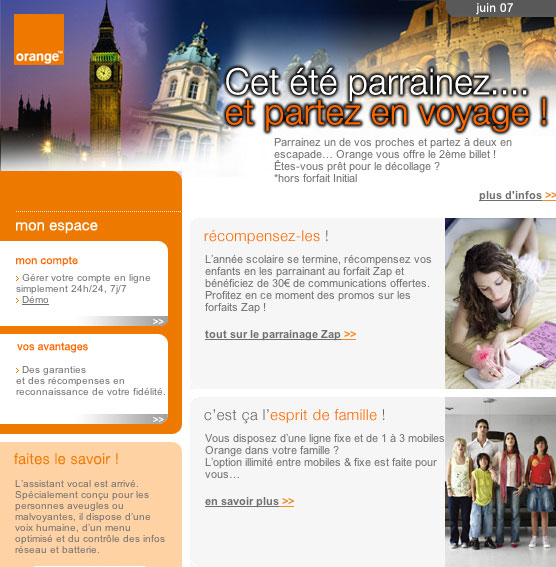
Comment définir la laideur. Une affaire difficile. Lorsqu’on regarde cette typo Helvetica «éclairé» par logiciel et ombrée floutée de même, n’importe comment, sans aucune élégance ni discernement, l’on en vient à se dire que le marketing direct sur le web est devenu l’affaire des amateurs et non plus des professionnels du graphisme. Mettez un ordinateur entre toutes les mains… Et alors, c’est bien, la modernité, la techno-démocratie. Qu’avons-nous à faire de compter des dizaines d’écoles d’Arts Graphiques dont aucun professeur n’aurait permis un tel massacre. Des centaines de DA et Directeurs de la Création qui n’auraient jamais laissé passé un «poulet» de la sorte. J’adore ce métier, tant il prolonge nos sensibilités artistiques, mais là quelle satisfaction, pour qui, pourquoi? Où est la charte graphique d’Orange, je veux la voir, la parcourir. Eh oui les designs-groups vendent très cher des chartes pour l’utilisation des logos mais qu’en est-il de l’aspect général et particulièrement de la typo des communications print ou web. Rares sont les dircoms qui supervisent dans le détail ces dévoyements taillés à la serpe. Mais si Orange continue, je vais changer d’opérateur, ç’est sûr. N’importe quel lecteur de ce blog aurait fait mieux, plus élégant, plus «propre», plus professionnel. Avis de tempête sur les services d’Orange. Cet été ne parrainez pas et partez qd même en voyage en emportant votre Bouygues ou SFR. Heureusement que les numéros de portables sont désormais devenus re-portables.
(remarque, je suis stagiaire en marketing et je ne l’aurai pas fait quand même. Peut-être cela vient-il de mes années d’Arts Appliquées qui s’avèrent dans la COM fortes utiles..?)
¶ peter: comme quoi un enseignement de culture graphique ne serait pas de trop dans les cursus marketing ;-)